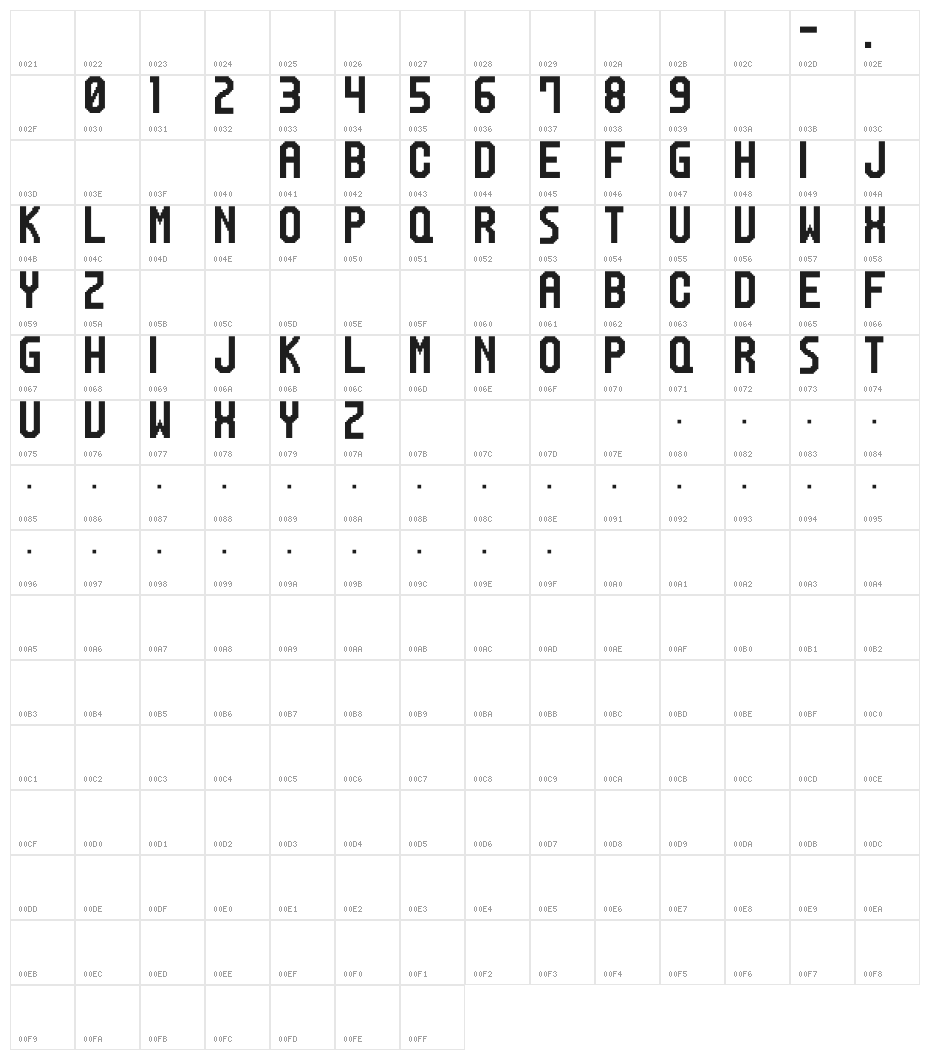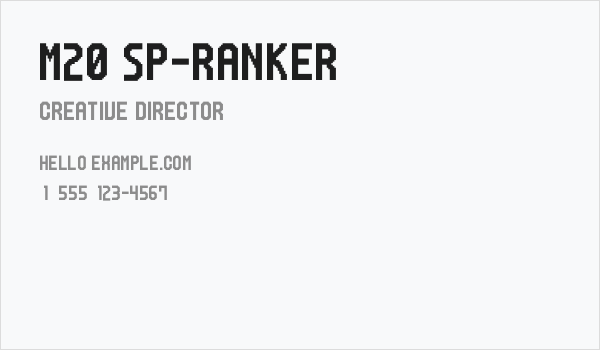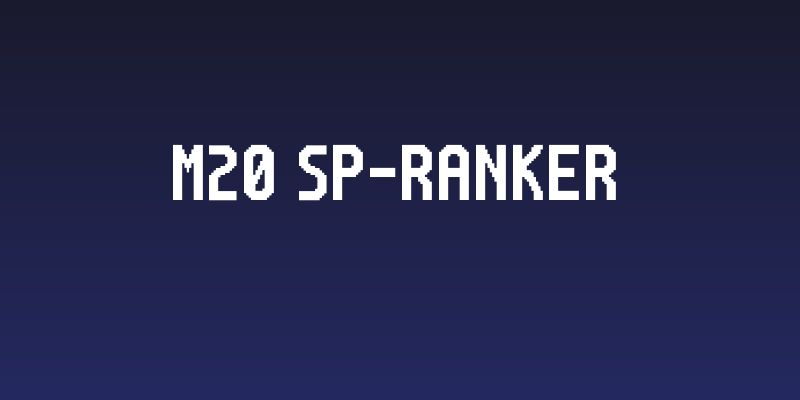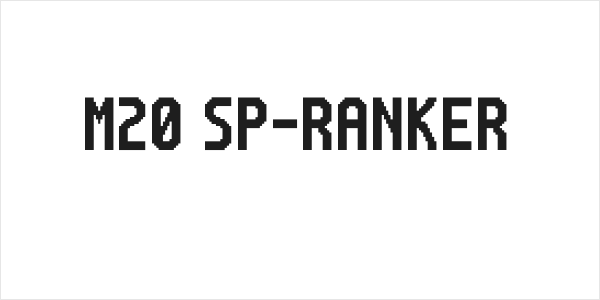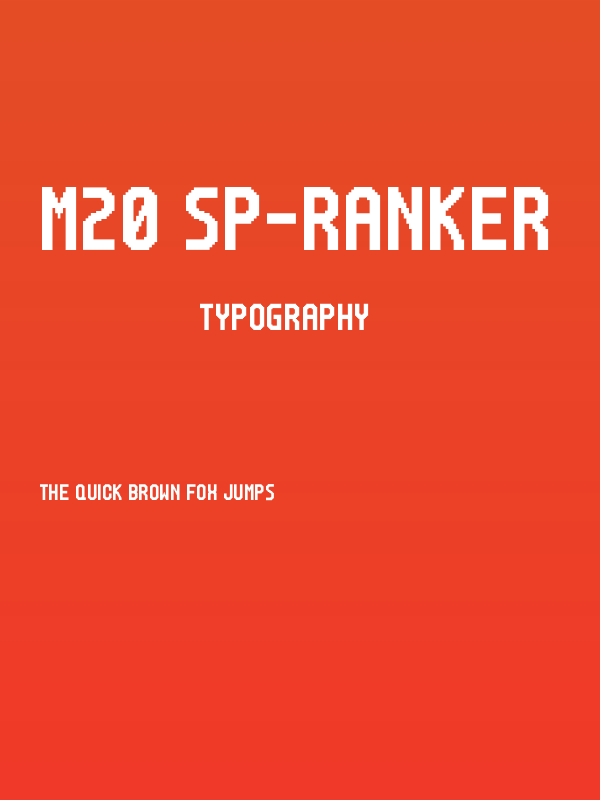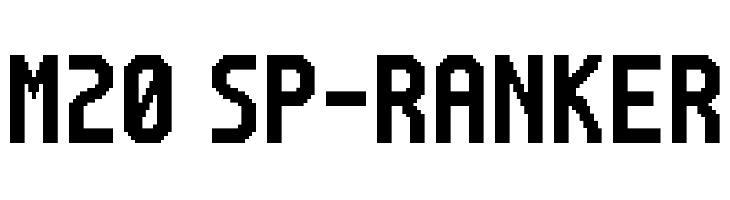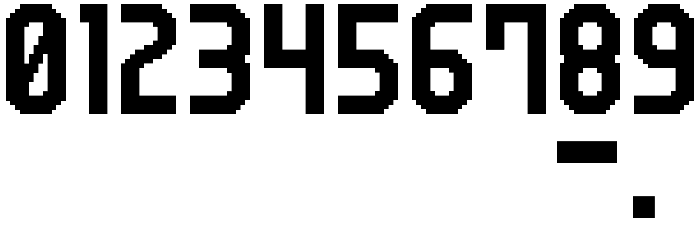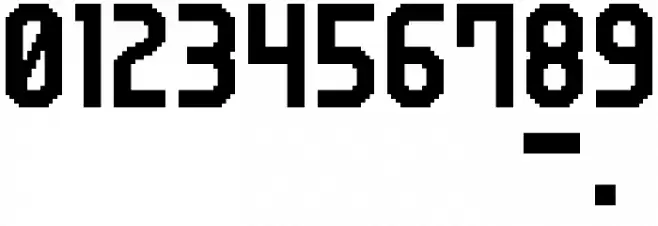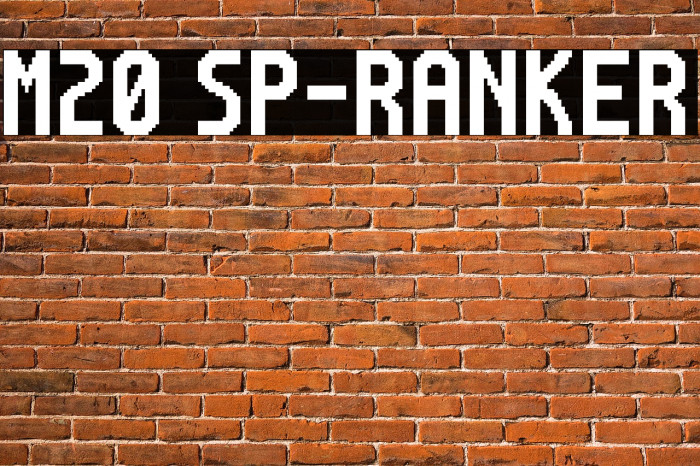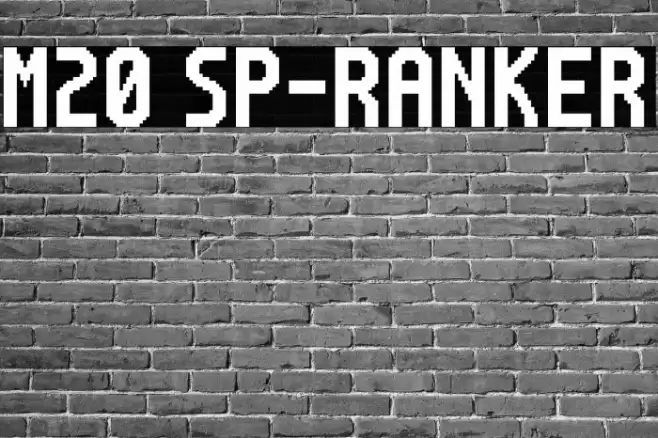
M20_SP-RANKER Font
| Categorie | Pixel |
| Stile generale | Retro, Digital |
| Caso d'uso | Headlines, Logos, Digital displays |
| Progetti proposti | Ideal for video game design, digital art projects, retro-themed posters, and tech-related branding. |